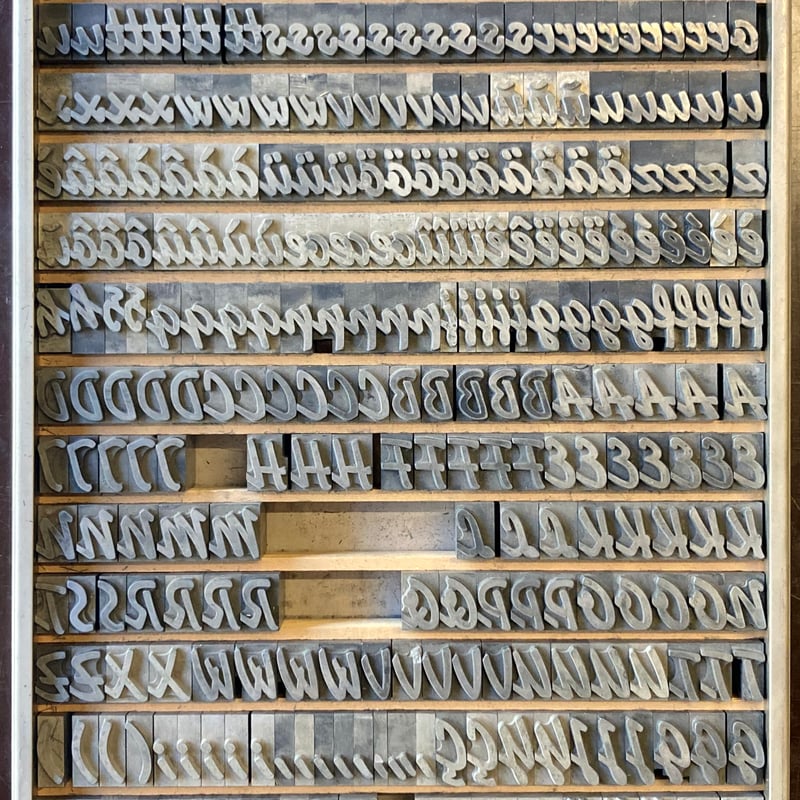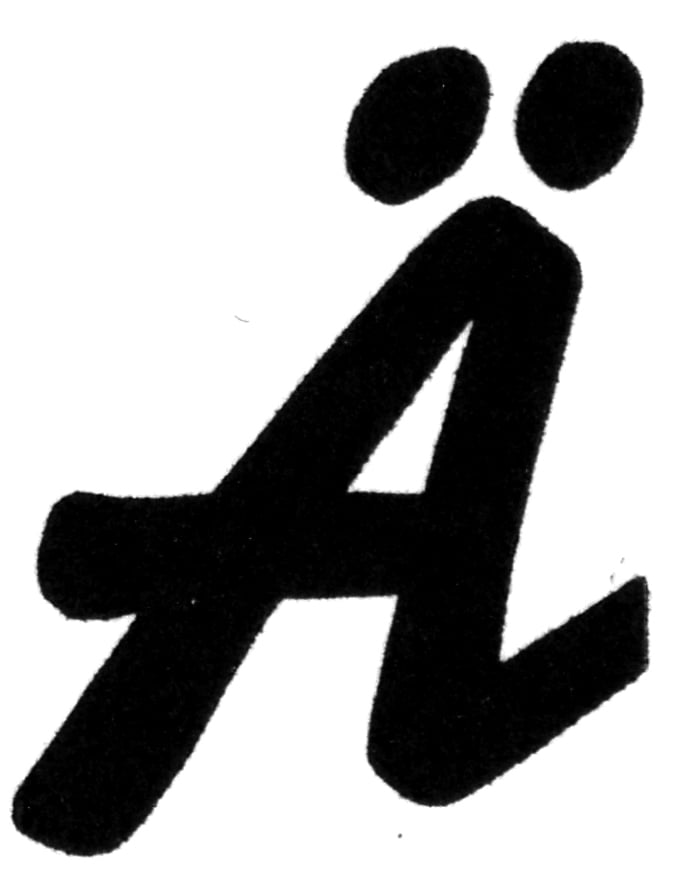
Signal Regular Italic
Druckmuster mit Text «Signal 48 pt»
Klassifizierung
Script
Schriftschnitt
Regular
Design
Walter Wege
Jahr
1931
Schriftgiesserei
Berthold
Von einzelnen Buchstaben wurden verschiedene Varianten angeboten (T, r, s, u, v), ab 1932 auch ein dünnerer und ein fetterer Schriftschnitt (siehe Fonts in Use).